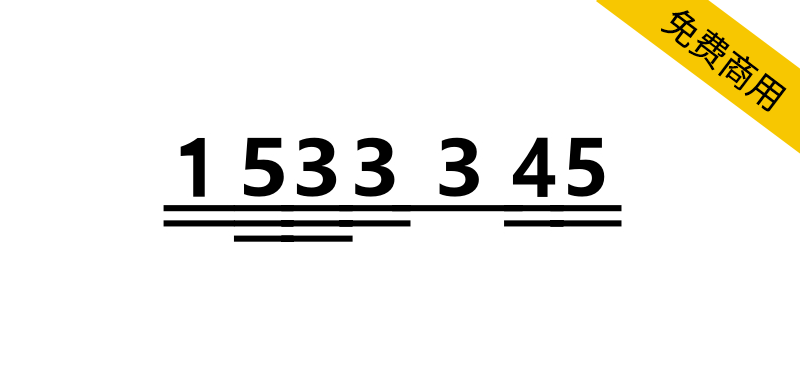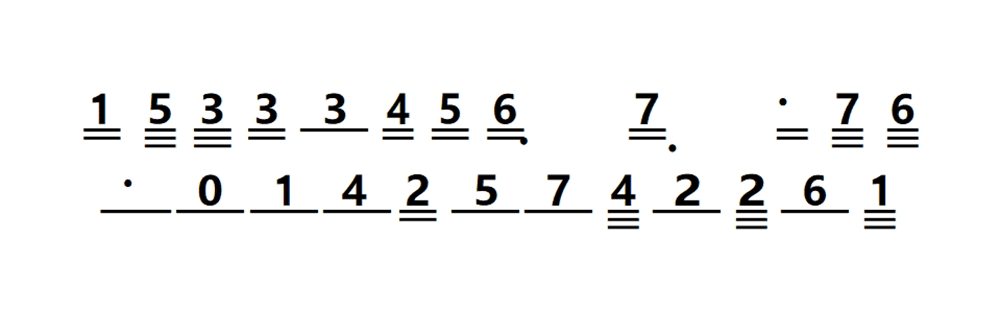
润植家昆曲简谱(等宽版和音长版)可能是世界上首个针对昆曲输入的免费可商用简谱字体系列哦!和其他商用乐谱字体不同,除常规简谱的符号输入外,我们的两款字体特点如下:
(1)可针对昆曲的常用腔格(撮腔叠腔之类可以通过常规简谱输入),尤其一般简谱不支持的腔格,如擞腔、豁腔等,可以很方便地输入。
(2)可以输入昆曲的常用板式符号,如4/4拍、2/4拍,甚至还有思凡的1/4拍。
(3)可以输入昆曲演唱的换气符号。
(4)可以输入昆曲非上板的无限延长符号。
(5)可输入昆曲的散板符号。
(6)采用不占位符输入音符的连线符号、高低音等。
(7)还有很多其他功能,欢迎大家自己摸索。
其中,等宽版适合单纯记录,适用于更偏美观的文字使用,一般大众和普通昆曲文字工作者可以使用;音长版更适合音乐人士使用,针对具体的音长,字符宽度不一样,最终,不管怎样输入,每拍的宽度是固定的,每小节的宽度也就是固定的,整个排版上,音符的宽度和唱腔音符的长度一一对应,所见即所得,有多宽那么就表示有多长,对于希望每一行有固定小节数(比如四小节)的排版工作者,非常推荐选用音长版。对于完全没有乐谱知识的朋友,用音长版版,反而有助于简谱的入门。不过,从美观上,音长版由于短音符的排版更瘦,可能会显得没有等宽版美观。
友情提示:等宽版和音长版的编码方式完全不一样,熟悉其输入需要一定的上手时间(尤其音长版的编码更复杂),所以,最终使用一种,需要忘掉另一种的编码方式,否则可能会记窜。
这个字体,虽然是针对昆曲输入使用的,不过也可广泛应用于其他乐谱的简单记录。比如京剧,如果不记录前倚音,单纯记录基本的乐曲旋律,也充分够用(但有些个性化曲谱记录过于繁复,比如有些京剧小生唱腔会标注下滑前倚音,本字体暂不支持——因为昆曲中的"口罕"腔一般也是个性化处理,不在曲谱中记录,所以昆曲字体通篇不用前倚音)。